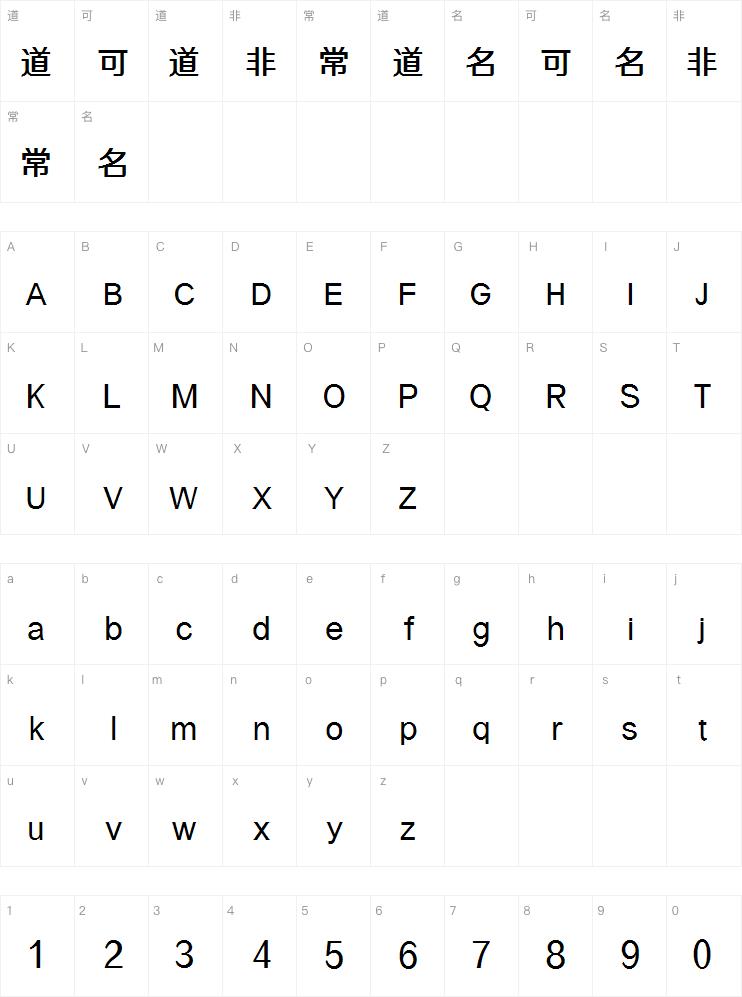
三极正典黑系列整体风格鲜明方正,字体结构干练简洁稳重大气,笔画平直、横细竖粗,撇捺镜像对称稳健。起笔收笔平直,折、钩转折明显,圆润饱满。它的灵感来源于黑体,又富有变化,庄重严谨的同时,具有婉转柔和的气质。视觉效果简洁易识别,实用性强。本作品适用于传统印刷媒介的标题与正文排版、各类平面显示及影视字幕等。